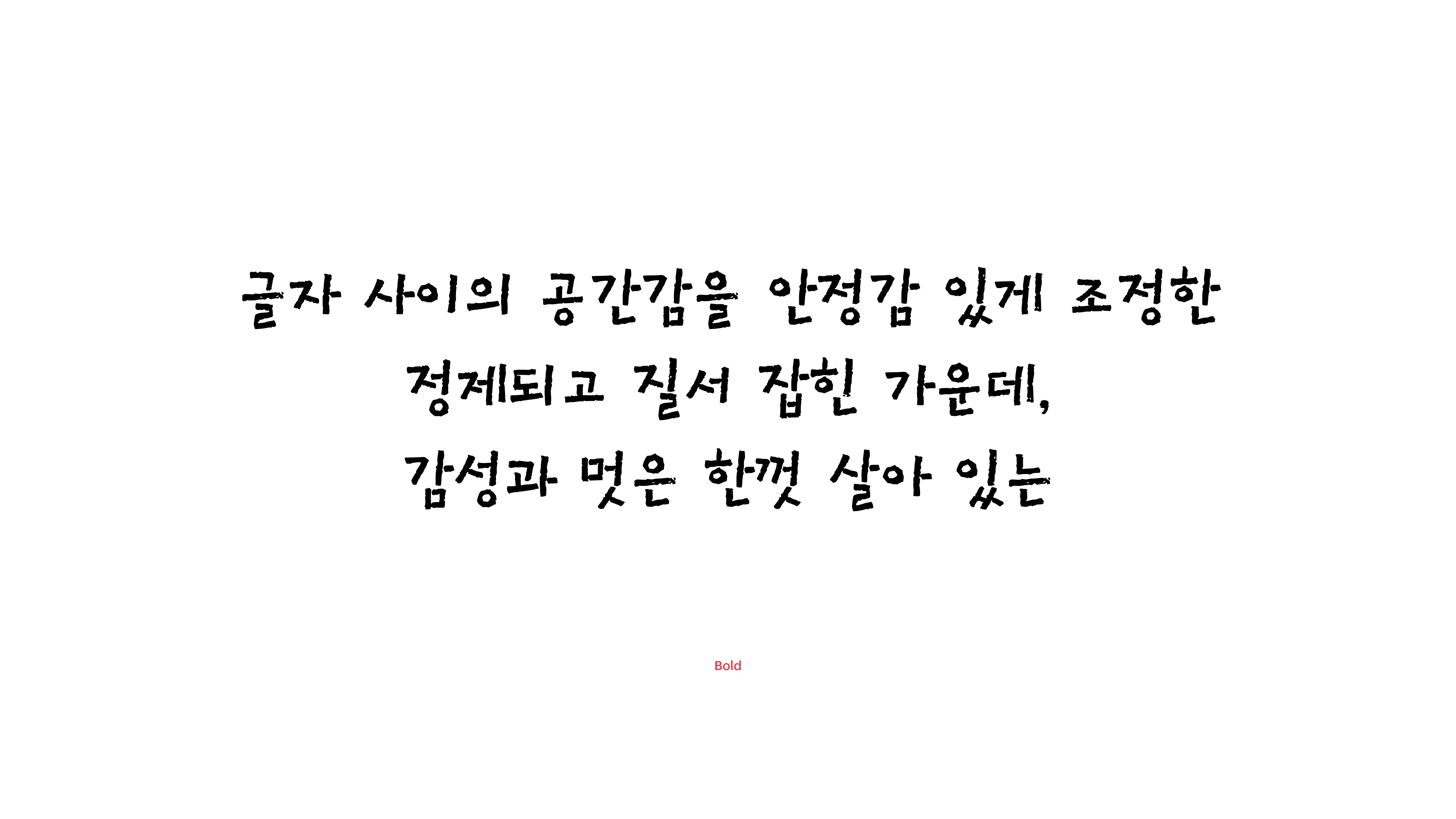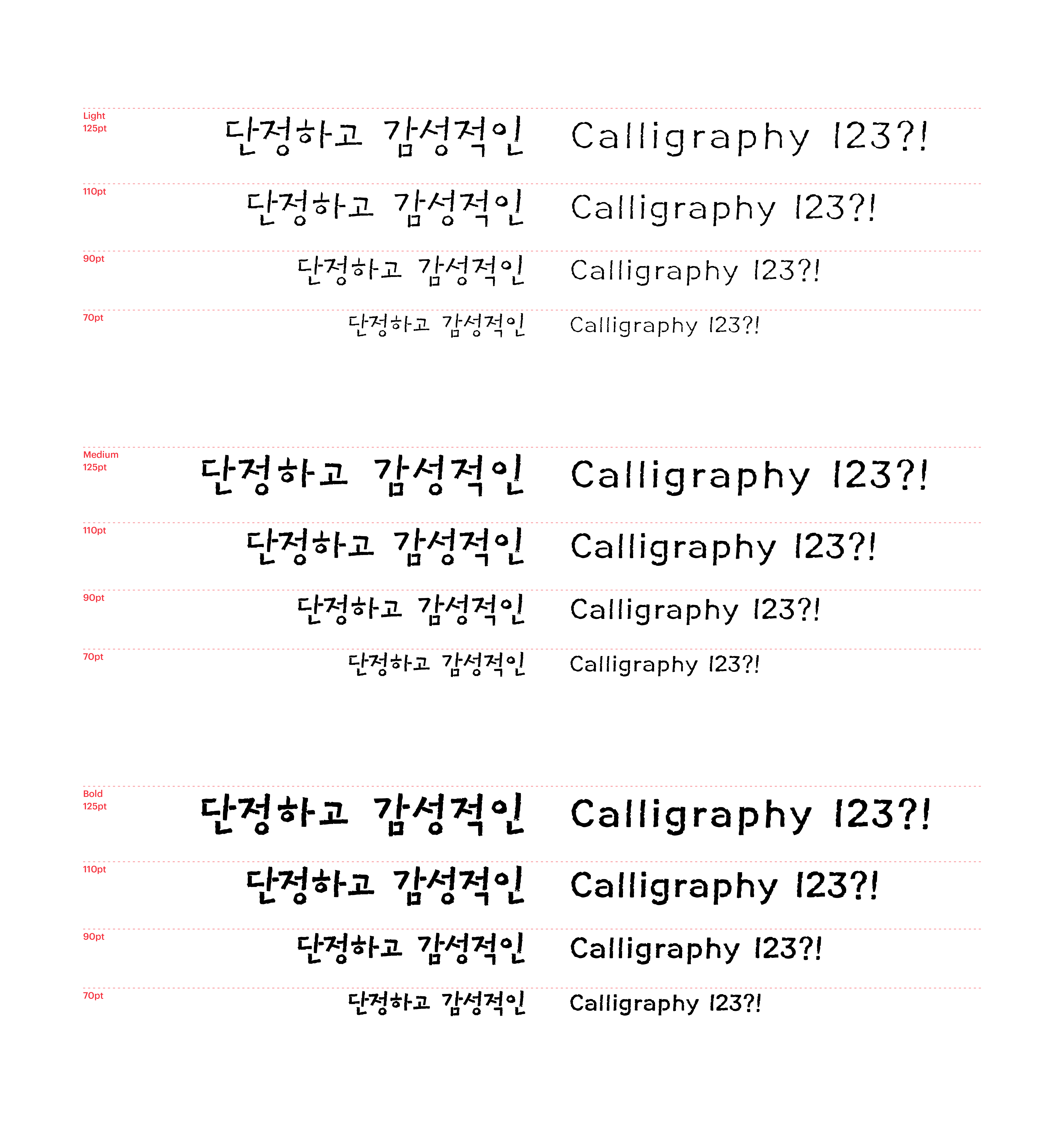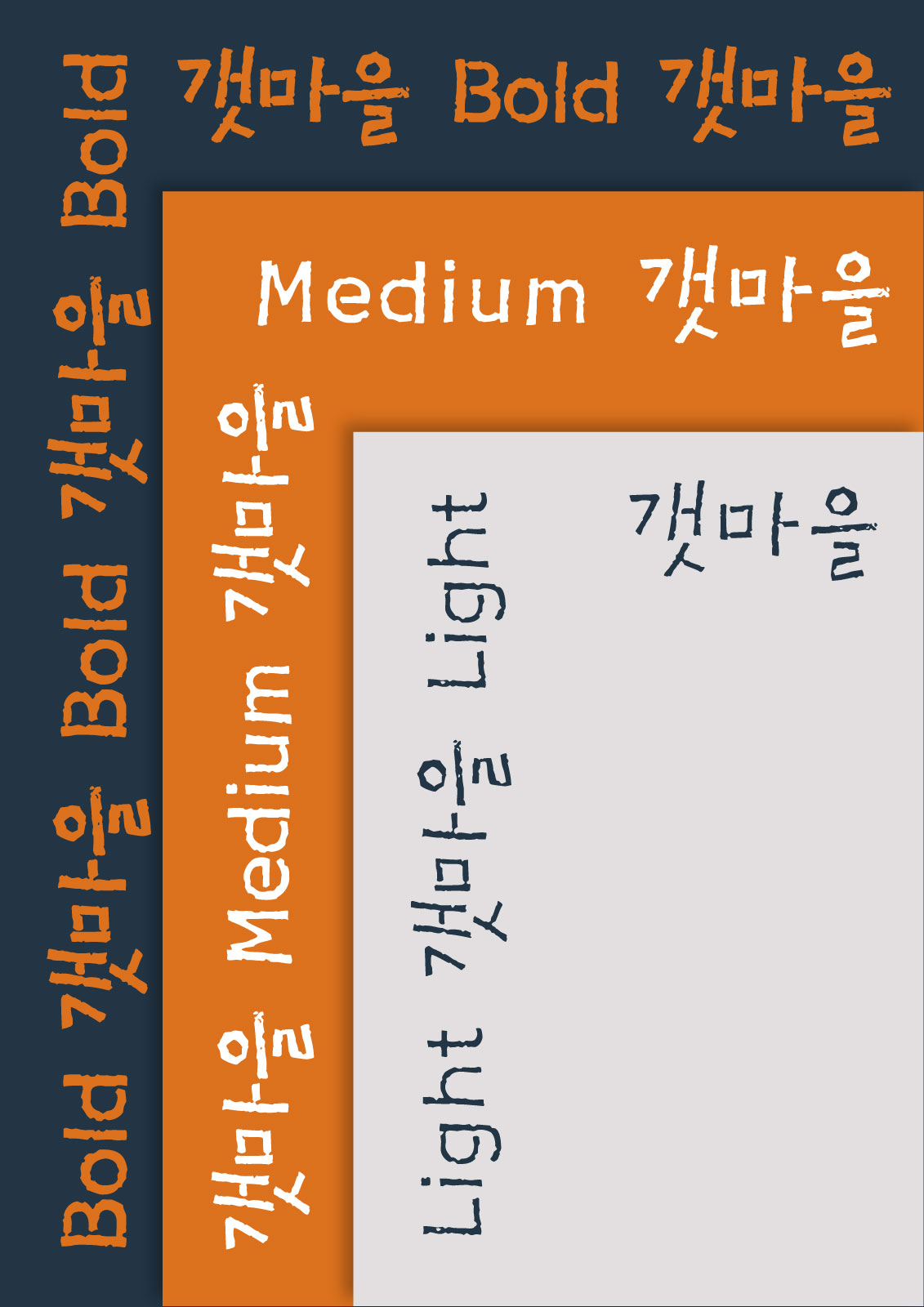
갯마을
Yoon 갯마을
단점이 있다고 해서 투덜대는 것은 하수의 태도입니다. 고수는 언제나 단점을 보완하기 위해 현명한 해결책을 강구하지요. 갯마을체는 손글씨 폰트의 약점으로 지적되곤 했던 글자 사이의 공간감을 안정감 있게 조정한 폰트입니다. 정제되고 질서 잡힌 가운데, 감성과 멋은 한껏 살아 있는 손글씨. 갯마을체의 깊이를 즐겨보세요.